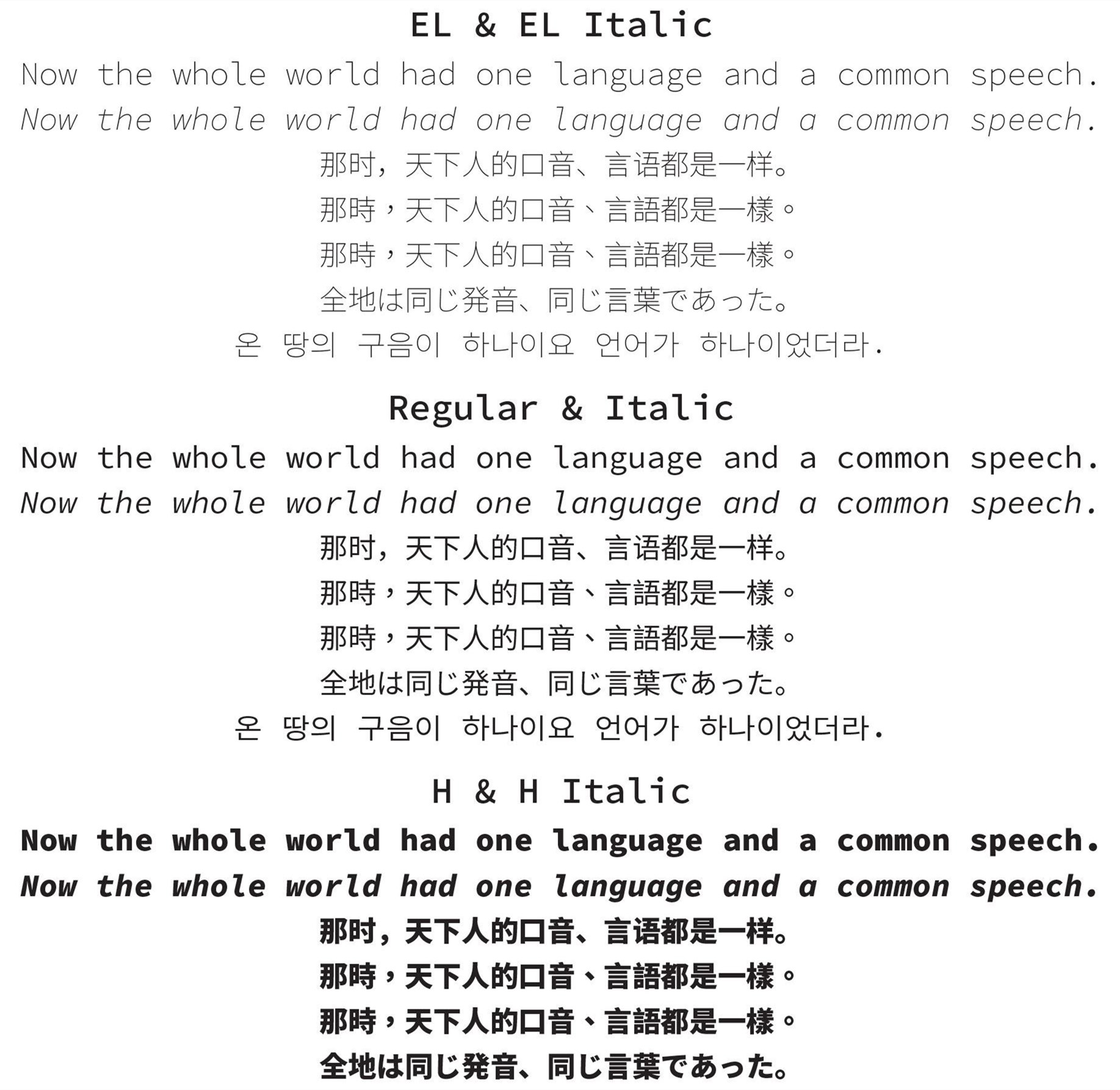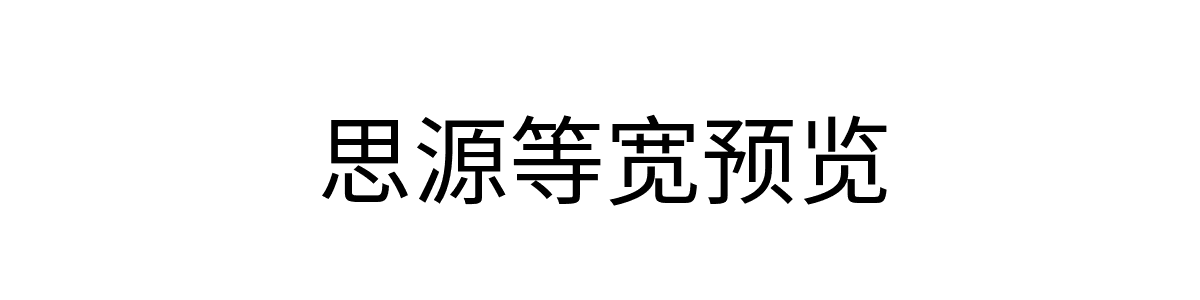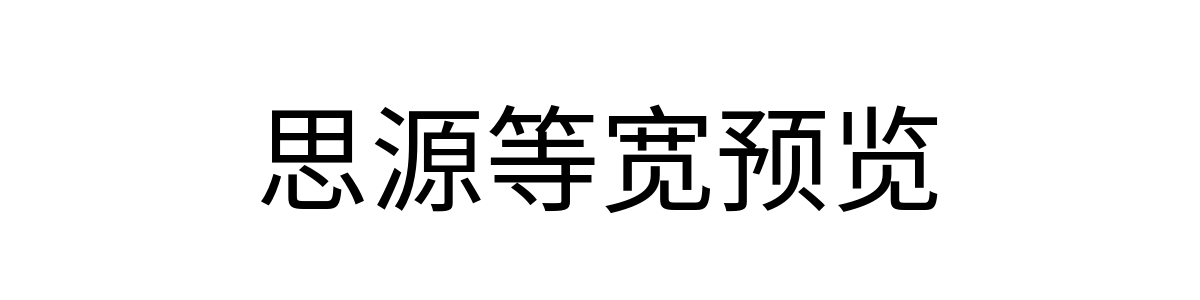
思源等宽
思源等宽(Source Han Mono)是 Adobe 推出的开源等宽字体家族,作为思源黑体系列的编程专用版本,解决了中日韩文字在代码环境中的显示一致性问题。该字体基于 Source Han Code JP 发展而来,西文部分源自专业的编程字体 Source Code Pro,汉字部分则继承思源黑体的优秀结构,形成真正意义上的泛CJK等宽字体解决方案。
字体严格遵循等宽设计原则,每个字符均占据相同宽度,确保代码对齐的绝对精准。整个家族包含7种字重(ExtraLight 到 Heavy)、5种语言变体(简体中文、繁体中文、日文、韩文等)及配套斜体,共70个字体实例,为开发者提供丰富的代码视觉层次选择。
字体风格
思源等宽的设计哲学在于功能性至上的精准与统一。其西文字符采用经典的等宽编程字体设计,确保字母、数字及符号在垂直方向完美对齐;中日韩汉字部分在保持等宽特性的同时,优化了字符间距与识别度,解决了以往代码中混合文字排版错位的痛点。
作为专为编程场景优化的字体,它舍弃了思源黑体中与编程无关的冗余字形,为西文斜体等重要编程特性腾出空间。这种设计使开发者在长时间阅读代码时能够获得清晰舒适的视觉体验,同时保持多语言代码注释的整洁美观。